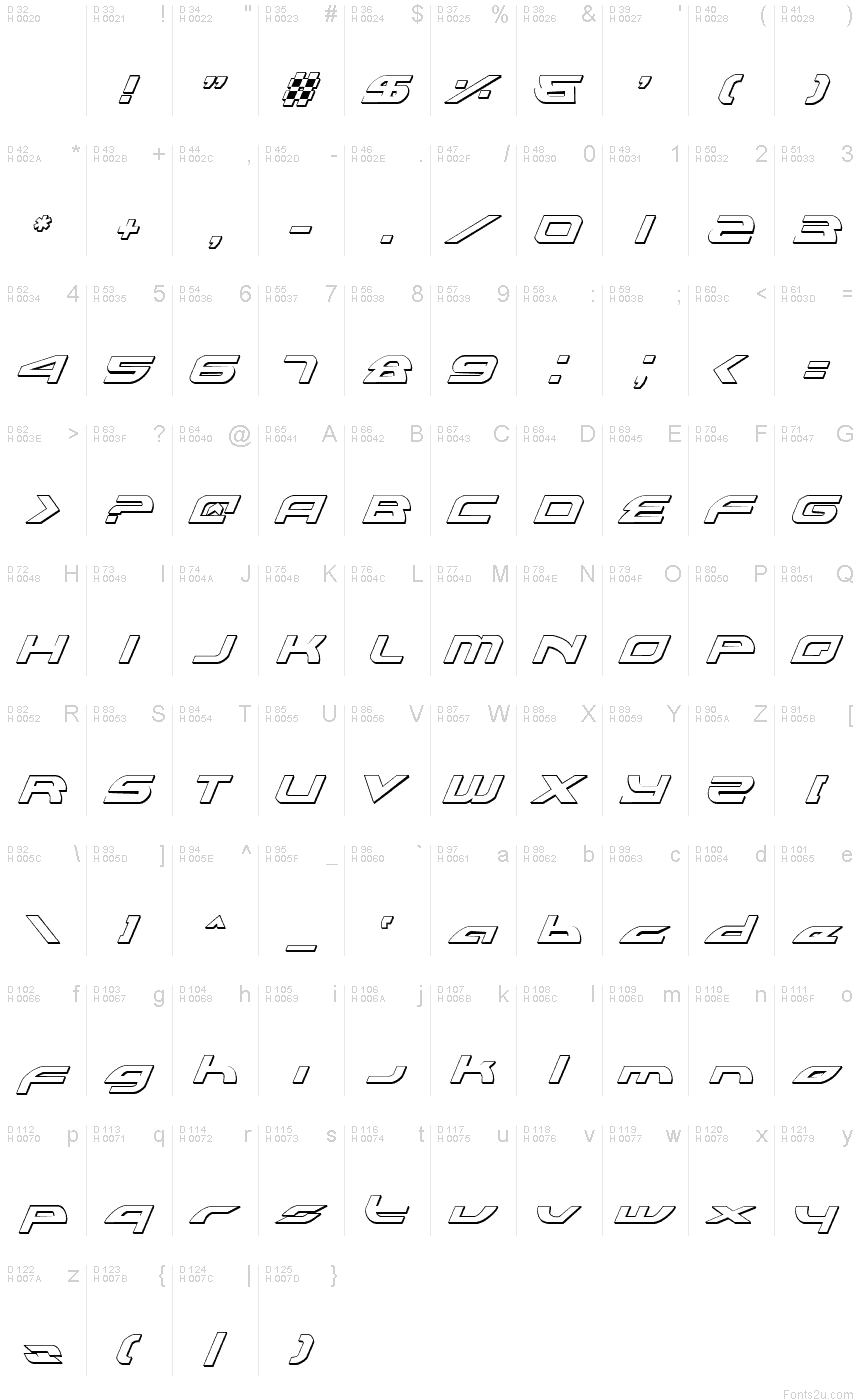
Alexis Lower Outline Italic di Iconian Fonts è un font display futuristico gratuito. Con la sua forte inclinazione a destra, le curve affilate e il design vuoto, ricorda le scritte di un bolide fantascientifico o di un cockpit al neon. Il DNA della famiglia Alexis è evidente nella sua geometria precisa, ma questo stile outline aggiunge una leggerezza e un senso di velocità che catturano l'attenzione senza appesantire.
Usa Alexis Lower Outline Italic per dare energia e dinamismo al branding di e-sport, copertine di libri sci-fi, poster di eventi tecnologici, interfacce di gioco, grafiche per YouTube o merchandise a tema racing. Questo font gratuito dà il meglio di sé nei grandi formati, dove i contorni angolari possono respirare; abbinalo a un sans neutro e pulito della famiglia Alexis o a un altro grotesk semplice per il corpo del testo, così da lasciare che il marchio rimanga il vero protagonista.